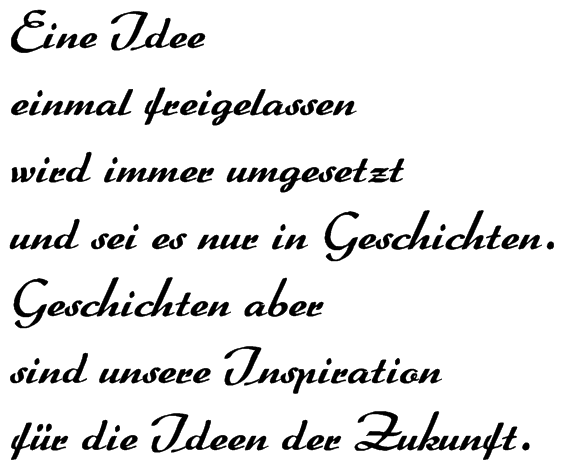
Auch mal hier ein Rätsel...
Heute habe ich mal schnell einen Font zusammenm geschustert, und da ich hier ja auf Vector-Magic aufmerksan gemacht wurde, und ich noch einen Probe-Trace frei hatte, habe ich da mal ein Schrift-Mustzerblatt durchgenudelt.
Nun ja, so richtig perfekt isses nicht, aber da hier unter den Download-Empfehlungen auch so eine schnell zusammengescannte Schrift angeboten wurde, die auch noch fehler in der Codierung hat, wage ich es mal, mei Tagwerk hier zu zeigen.
Das Rätsel dabei: wie bin ich als Namen wohl auf „Rumburak“ gekommen. Tip: wer die Schriftart erkennt, die ich da eingescannt und getraced habe, dürfte auf die Lösung (vielleicht) kommen
Was meint Ihr? Irgendwie brauchgbar, oder totaler Müll, und besser löschen?
Das ist die Arabella von Arno Drescher, die hatten wir ja erst kürzlich.
Da es bereits eine tolle Digitaliserung der Schrift gibt, glaube ich nicht das man eine weitere und zudem schlechtere Digitaliserung benötigt.
Treffer!  Und ja, du hast recht, war auch nur ein Test, ob dieser (Vektor) Zauberer so gut ist, wie diew Leute sagen, und da ich noch einen Probeschuss hatte, hab ich es daran mal getestet.
Und was diesen digitalen Rumburak anbelangt, bin ich mir sicher, mir da keinen Zugang zu leisten, lohnt nicht, Die Zeit, die man in so eine Vektorisierung stecken müsste, um daraus wirklich gute Konturen zu machen, im Vergleich das lieber gleich sauber von Hand zu zeichen, und dann noch Geld fürs tracen? Nö!
Autotrace braucht offensichtlich so ideale Vorlagen, und das sind dann eben keine Scanns, sondern so saubere Drucke von Vektordaten, die man dann auch leicht nachzeichnen kann.
Also schicke ich Rumburak zurück ins Märchenland!
Ähm, da hat der gute Dieter aber n noch schlechterten Vektorisierer erwischt :-( Da stimmen die Strichstärken ja gar nicht.
ich habe vectormagic früher mal genutzt als es noch kostenfrei war und dann später nochmal zum testen. da empfand ich das es die gleichen ergebnisse wie die vektorisierungsfunktion in illustrator lieferte.
Ja, die kochen eben auch nur mit Wasser, und die ganzen Programme krabbeln eben doch nur an den Pixeln herum, ohne wirklich das Bild zu „sehen“.
Nun ja, ein bisschen schöner, als andere Tracer sind die ergebnisse schon, aber noch immer meilenweit von den Versprechungen weg, leider...